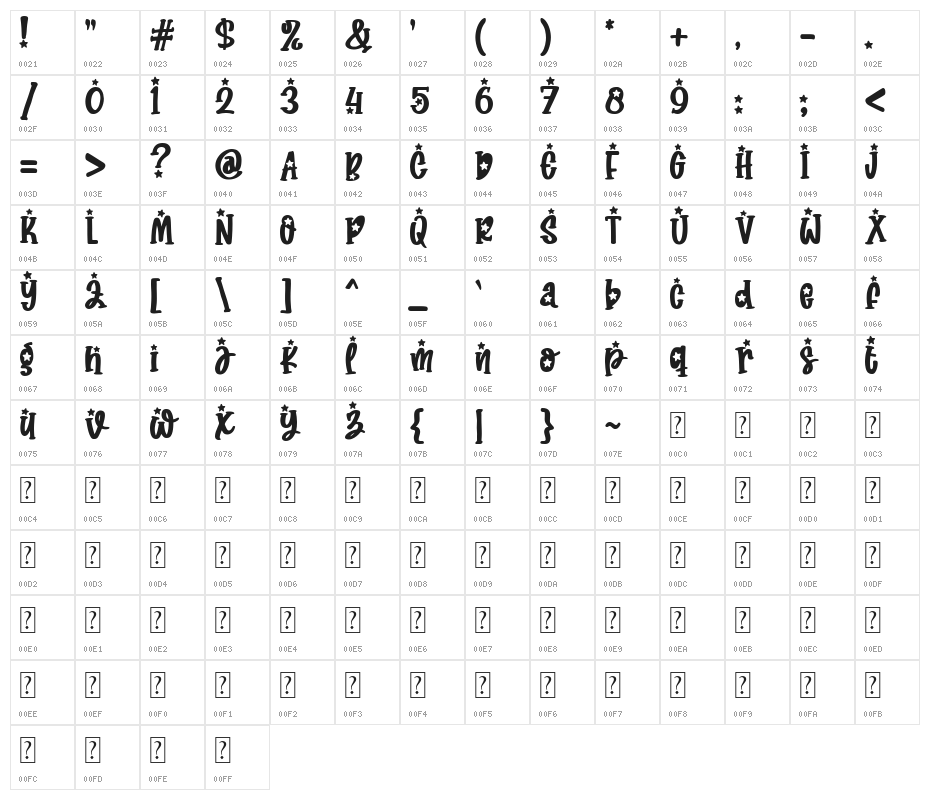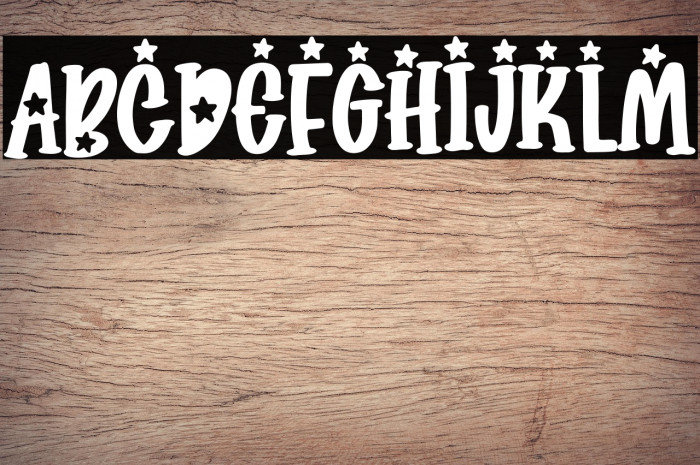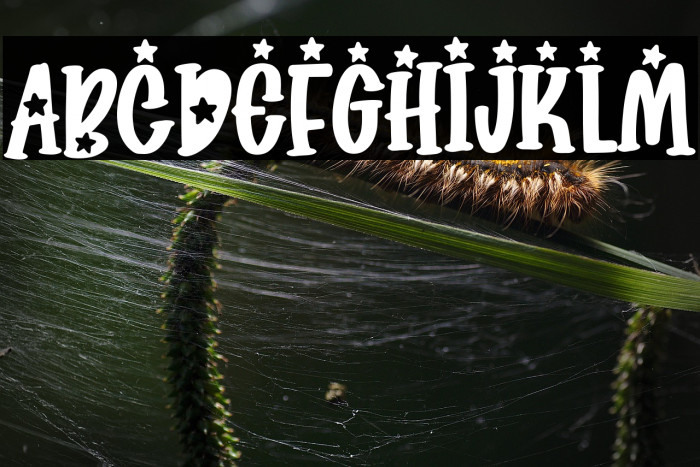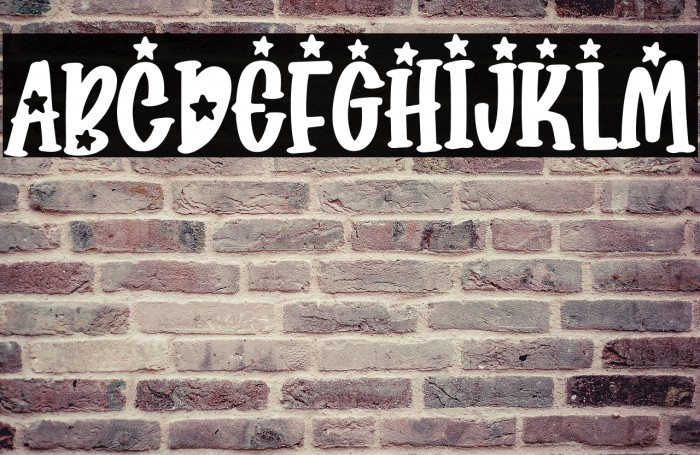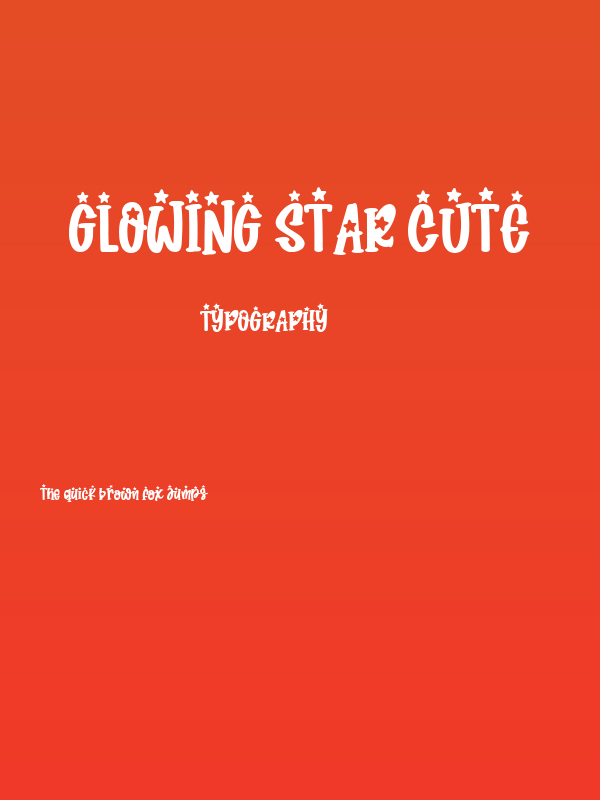
Glowing Star Cute Font
✎ Cartoon
Fonts by Subectype & Orenari
| مشاريع مقترحة | Ideal for children's books, party invitations, playful branding, and creative posters. |